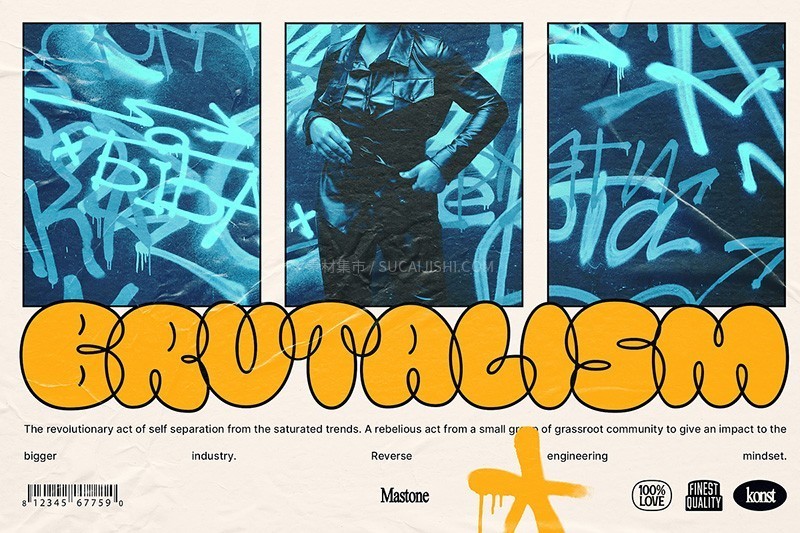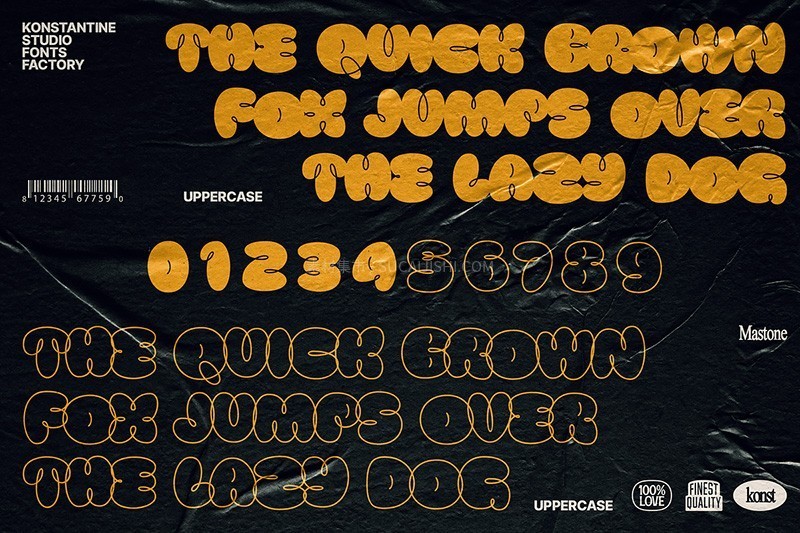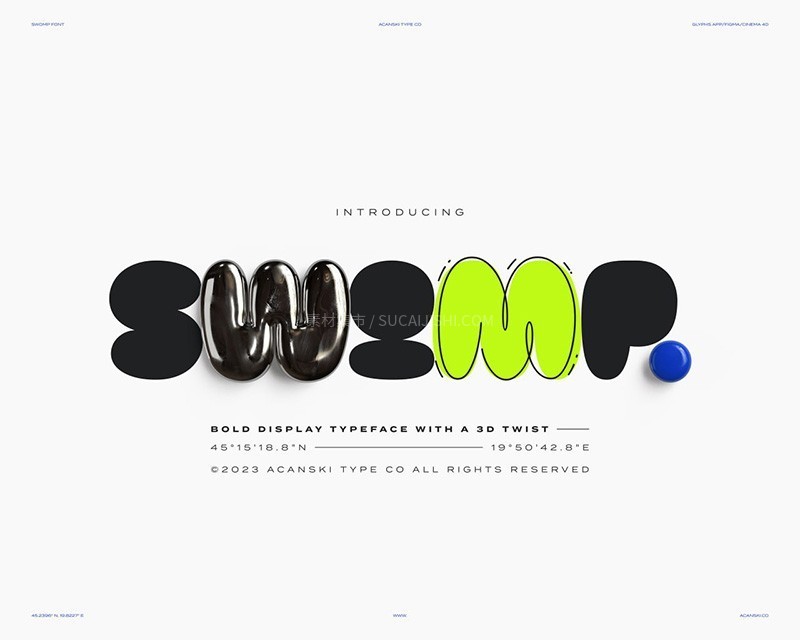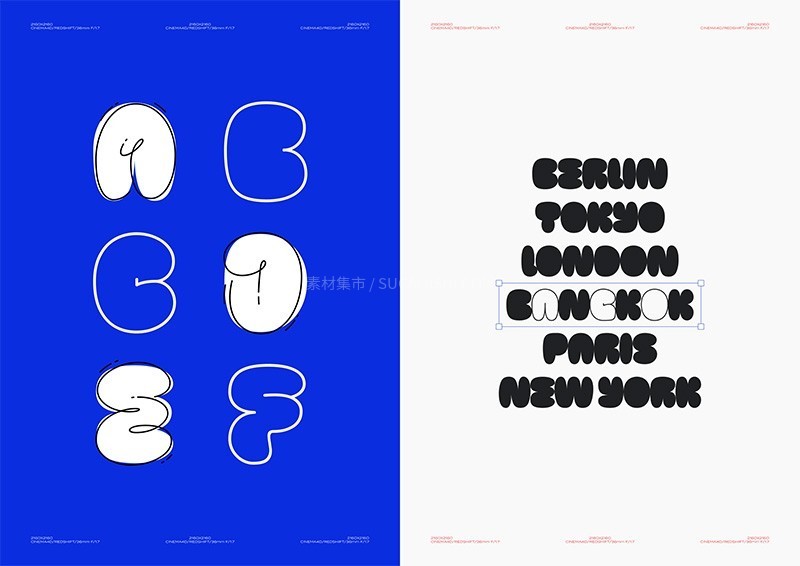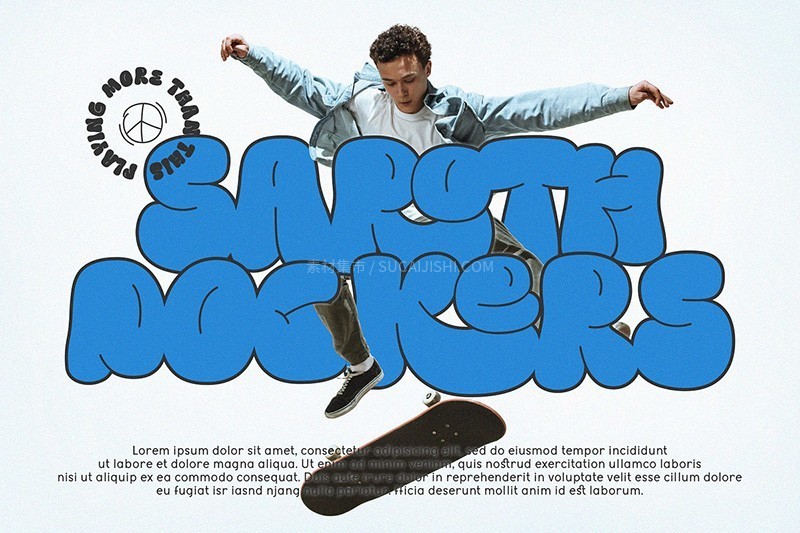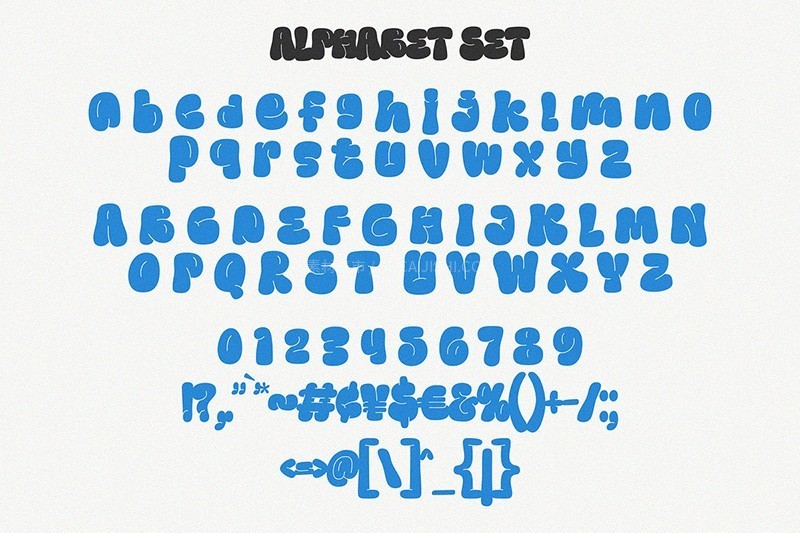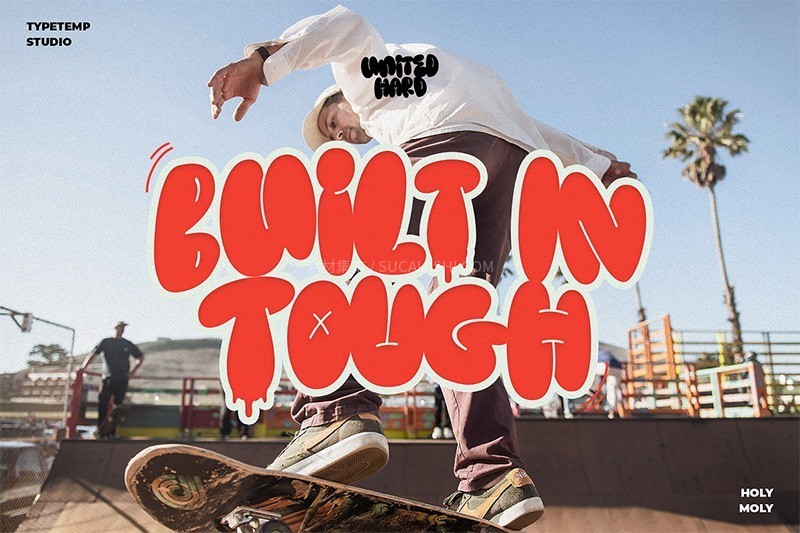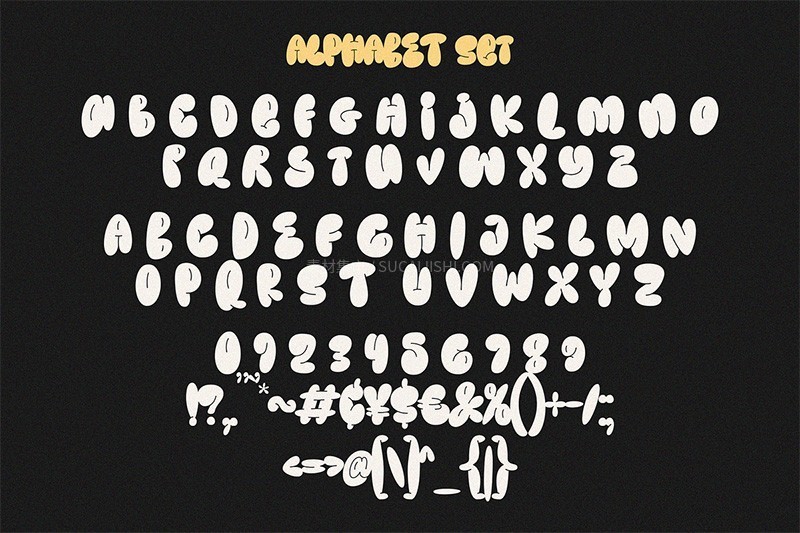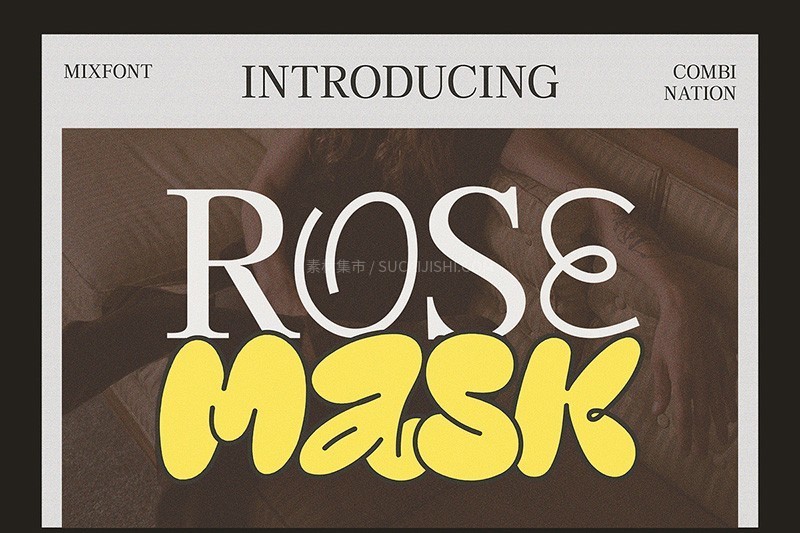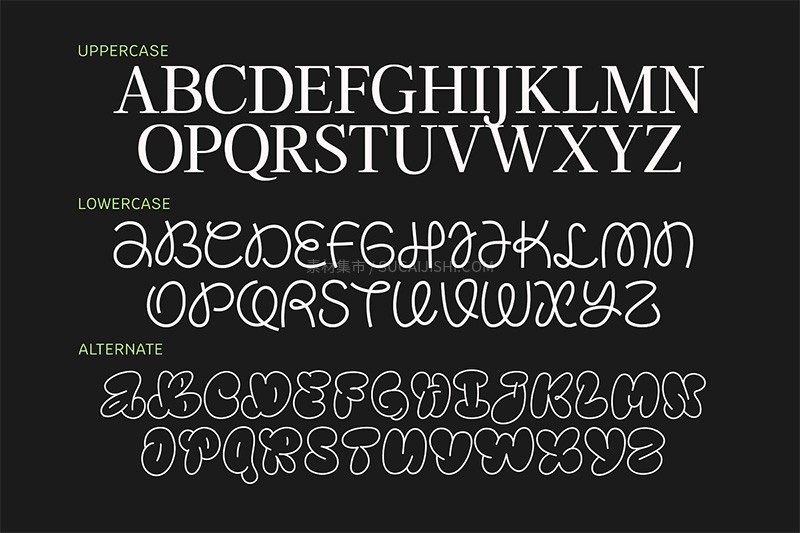
10款气泡涂鸦英文字体合集
平面设计师都在用的潮流字体!这款气泡涂鸦风字体,完美融合Y2K的趣味、街头的活力、野兽派的硬朗,带来前所未有的视觉冲击力。非常适合时尚品牌、潮流服饰、个性商品等各种需要突出年轻活力和独特风格的设计项目!
Mastone
一款具有圆润、饱满的字形,类似于气泡或充气效果。带有手绘或涂鸦的痕迹,呈现出随性、自由的视觉感受。适合用于需要表达年轻、活力、趣味和街头文化相关的设计中。
Swomp
这款充满童趣的泡泡字体,融合随性的涂鸦笔触,为儿童派对邀请函、生日贺卡、手工DIY项目增添一份活泼与温馨。
Stuinwey
一款极具个性的气泡涂鸦风格字体,将街头文化的自由奔放与泡泡字体的圆润可爱完美结合。
Yerk
这款现代字体灵感来源于Y2K潮流,拥有常规、斜体和倾斜三种样式。其粗犷的字重、方形的字母和略微圆润的边角,能为你的设计增添强大的视觉冲击力和独特的个性。
Holymoly
一款具有涂鸦气泡风格的字体。不仅拥有个性的涂鸦气泡造型,还包含了多种替代字体和连字符,方便你进行更灵活的排版和设计。
RoseMask - 3in1 组合字体
RoseMask 是一款极具创意的组合字体,为你提供了前所未有的设计灵活性。它巧妙地将三种独特的风格融为一体这款多功能字体可以轻松混合搭配,在优雅和俏皮之间自由切换,是品牌设计、编辑排版等各种设计项目的理想选择。
Bubblicity
Bubblicity 字体系列是一款充满乐趣和创意的俏皮字体!它包含了6种不同的风格,其设计灵感来源于充满魅力的Y2K时代和充满力量的街头涂鸦,并巧妙地融入了飞舞的线条元素。
Morefine
这款俏皮而充满活力的字体,将涂鸦艺术的奇思妙想带入生活。它采用圆润而膨胀的字体形式,模仿肥皂泡在空中漂浮的可爱外观。
Bulbis
这款独特的泡泡字体灵感来源于充满活力的涂鸦和街头艺术,融合了当下流行的Y2K文化和街头服饰视觉效果,能为你的作品增添新鲜和现代的气息。
Urbanicity
一款多语言字体,包含6种风格,非常适合用于海报、卡片、社交媒体帖子、邀请函和其他艺术作品,你甚至可以将其用作Logo字体。